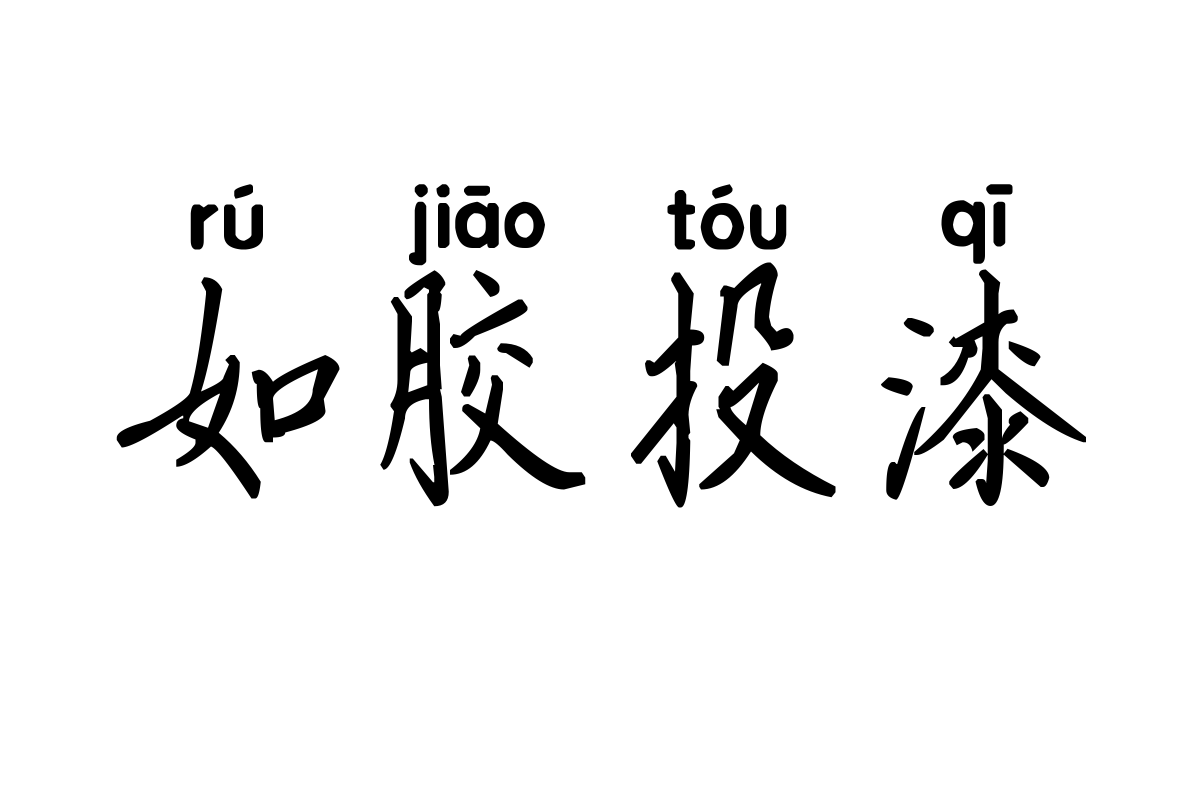
米开光阴荏苒是一款具有独特设计元素的字体,它由著名设计师米开朗基罗·恩里克·康多提创作。这款字体以其简洁、现代的线条和独特的结构而闻名,给人一种强烈的视觉冲击力。
米开光阴荏苒字体的特点是其独特的笔画形状和流畅的线条。它的每个字符都经过精心的设计,使得整体看起来既有艺术感又不失实用性。这种字体适合用于各种场合,如广告、海报、网站等,能够为作品增添一份独特的魅力。
除了其独特的设计元素外,米开光阴荏苒字体还具有很高的可读性和易用性。它适用于多种字体大小和排版方式,无论是在网页还是印刷品上都能够展现出良好的视觉效果。此外,这款字体还具有较高的识别度,能够在众多字体中脱颖而出,让人过目难忘。
总之,米开光阴荏苒是一款非常优秀的字体,无论是从设计、可读性还是实用性方面来看,都值得您尝试使用。如果您需要一款独特、有艺术感且易于使用的字体,那么米开光阴荏苒绝对是一个不错的选择。